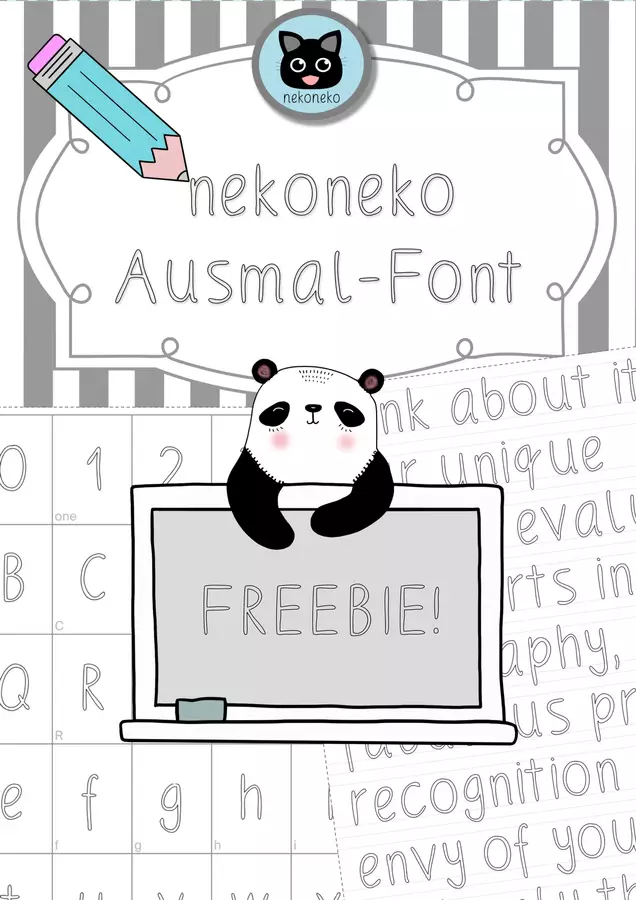
Neu auch als Ausmal-Schrift :-) . Ich habe mich bei der Ausmal-Schrift auf die üblichsten Glyphen beschränkt. D.h. A bis Z, 0 bis 9 , Frage- und Ausrufezeichen sowie Punkt, Doppelpunkt, Komma.
Immer wieder bekomme ich liebe Komplimente für meine Handschrift an der Wandtafel von meinen Instagram-Posts zum Wort der Woche. Darum habe ich nun meine Schrift digital aufbereitet, um sie euch gratis zur Verfügung zu stellen!